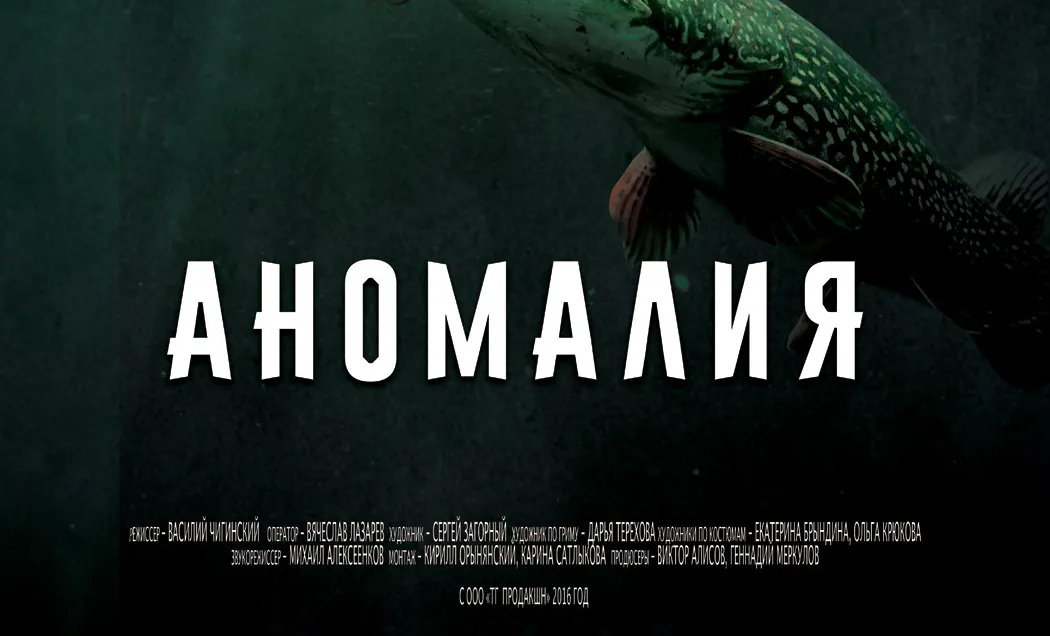
First One Stripe Font Family
Introduzimos First One Stripe! É uma família de 5 tipografias de sans-serif elegante e contemporânea projetada por D’Astakhov. First One Stripe é um conjunto de tipos arquitetonicamente limpos e estilizados, inspirados na geometria geométrica moderna europeia, oferecendo aparência harmônica tanto para textos quanto para headlines. Seu design atemporal combina perfeitamente com a comunicação visual contemporânea, sendo particularmente adequado para marcas de marca, editoriais e sinalização. Além disso, George Sans é um parceiro perfeito para aplicações maiores, proporcionando um texto fluido e elegante, ideal tanto para uso em aplicativos digitais quanto impressos. Com First One Stripe da D’Astakhov, você encontrará uma solução que se destaca pela sua contemporaneidade e beleza moderna.